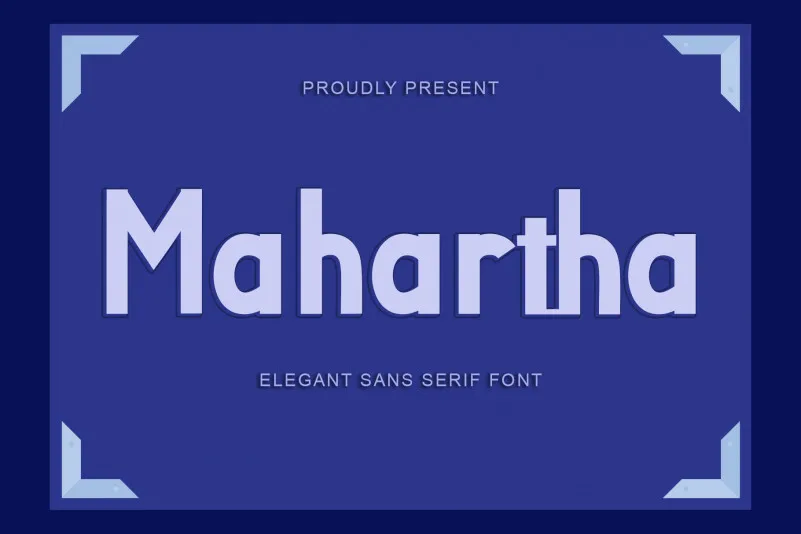
A Mahartha Font é uma escolha perfeita para quem busca simplicidade e modernidade no design do seu site ou material impresso. Ela é uma fonte sans-serif criada pelo designer Yoga Letter, com um aspecto clean e elegante que se adapta perfeitamente a qualquer projeto digital ou impresso. Com linhas leves e formas retas, a Mahartha traz uma sensação de leveza e conforto ao texto. Ideal para situações onde você precisa de uma fonte legível e moderna sem deixar espaço demais entre as palavras. Além disso, a sua tipografia suave não só ajuda na leitura, mas também adiciona um toque de sofisticação aos seus materiais. Seja para websites responsivos, sites profissionais ou design gráfico do dia-a-dia, essa fonte é uma ótima opção. Ela combina perfeitamente com designs modernos e contemporâneos sem perder a essência do trabalho cuidadosamente planejado. A Mahartha representa o equilíbrio entre simplicidade e elegância, tornando-a uma escolha versátil para designers de todo tipo.